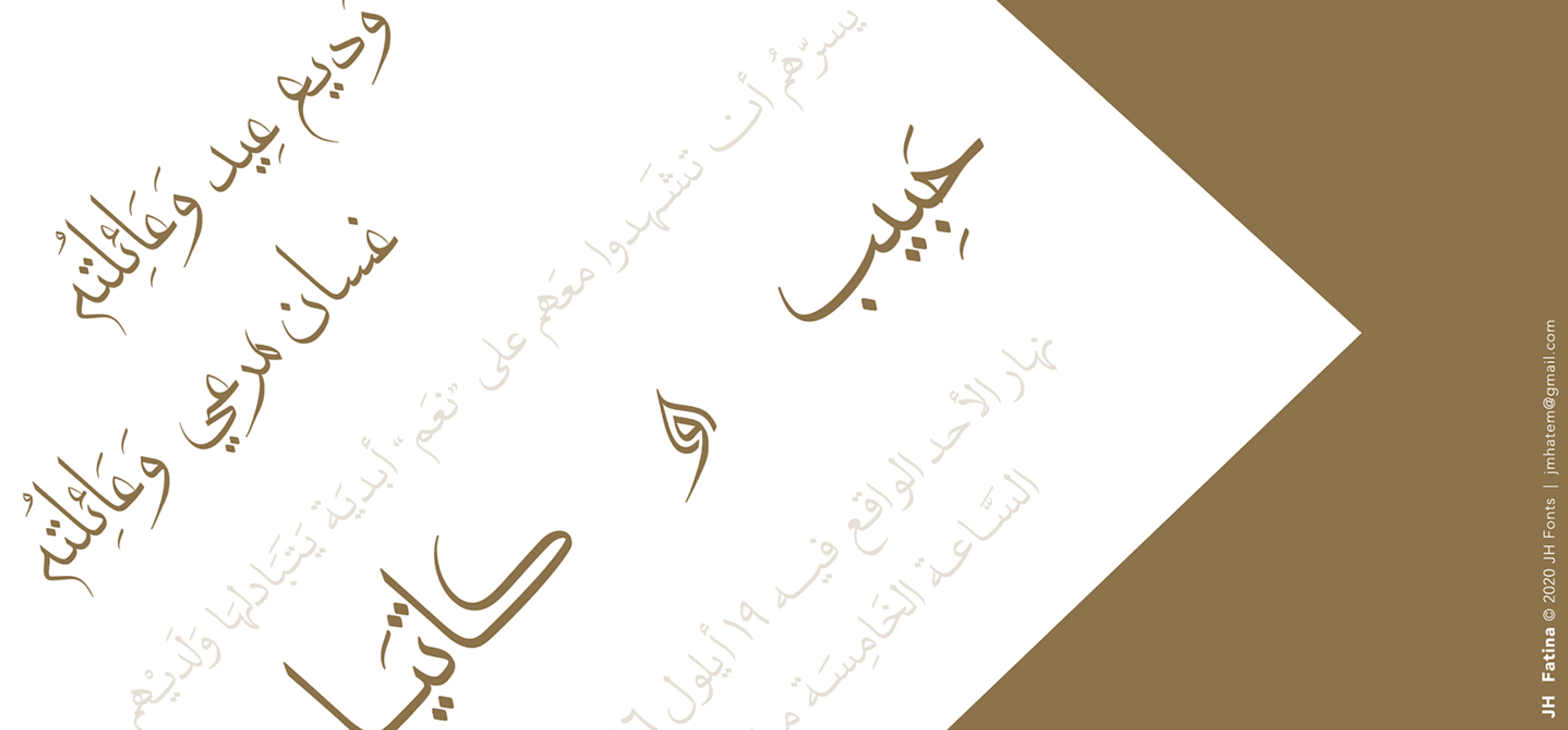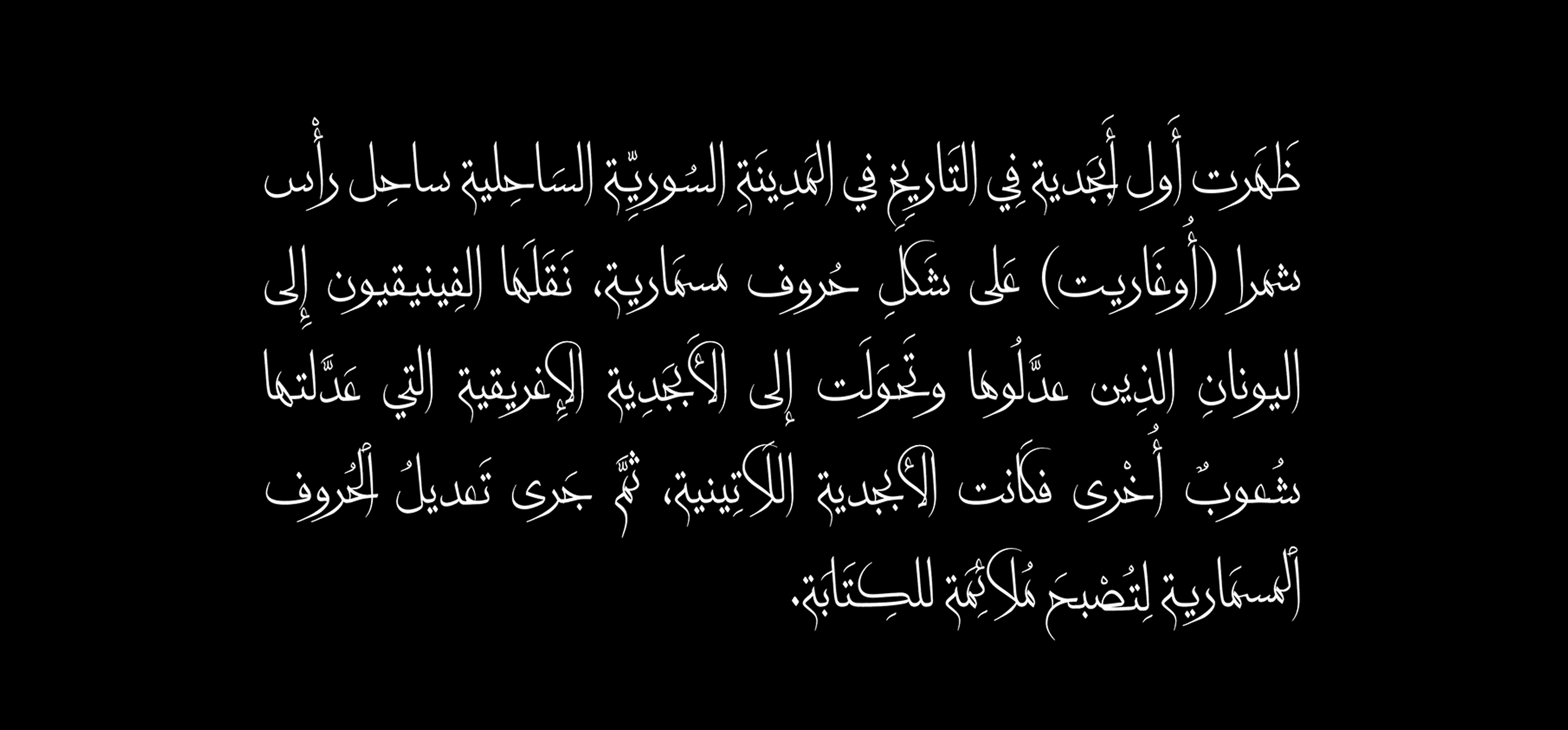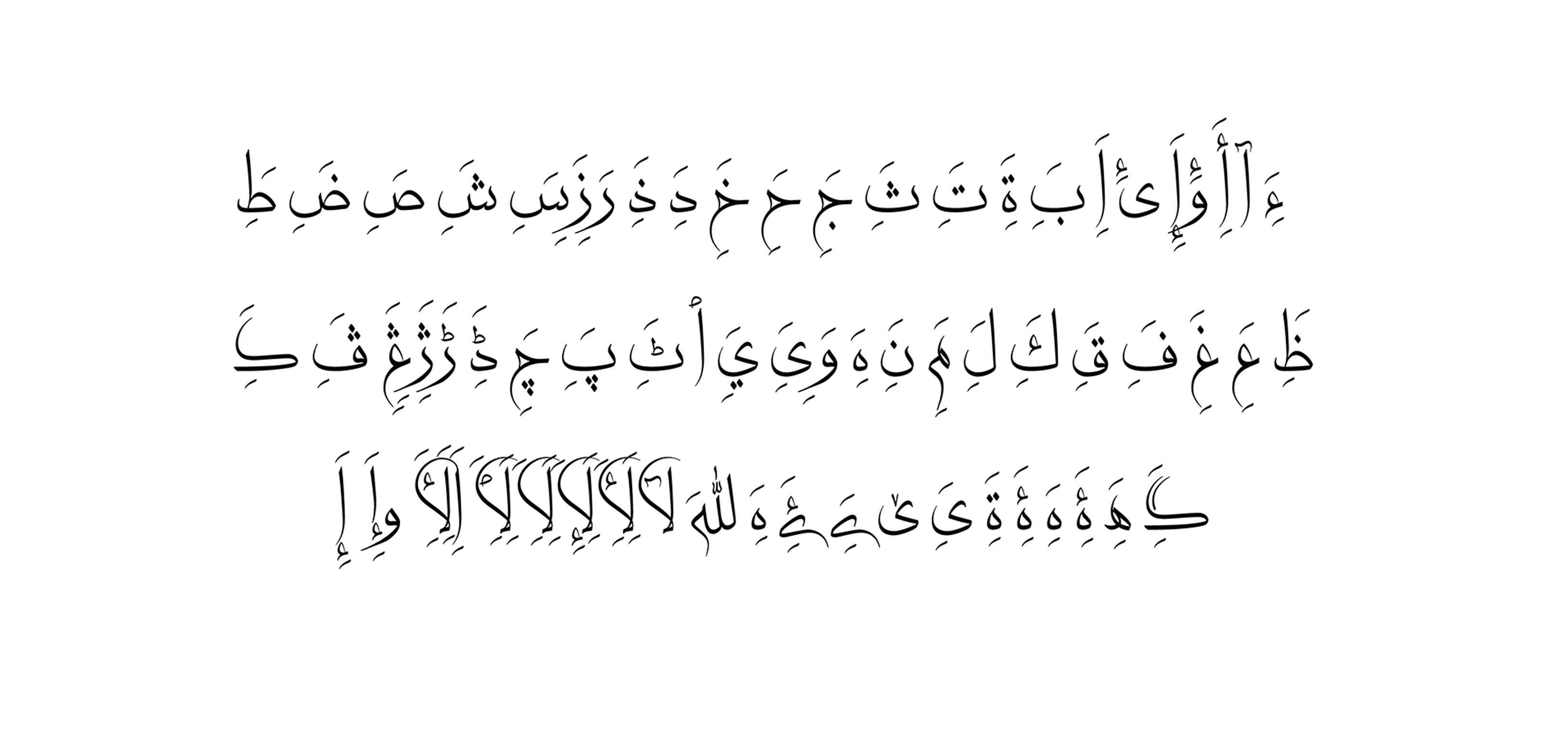
خط عربي تم تصميمه دون التقيد بقواعد خطية محددة، حيث تم استلهام حروفه من الخطوط التالية: السنبولي، النيسابوري، الديواني، والثلث.
يحتوي على أكثر من 1300 حرف إضافي لمحاكاة الخط العربي اليدوي الحقيقي وتعزيز جمال الخط.
يُعد JH Fatina مثالياً لبطاقات التهنئة والزفاف، عناوين الكتب، والشعر.